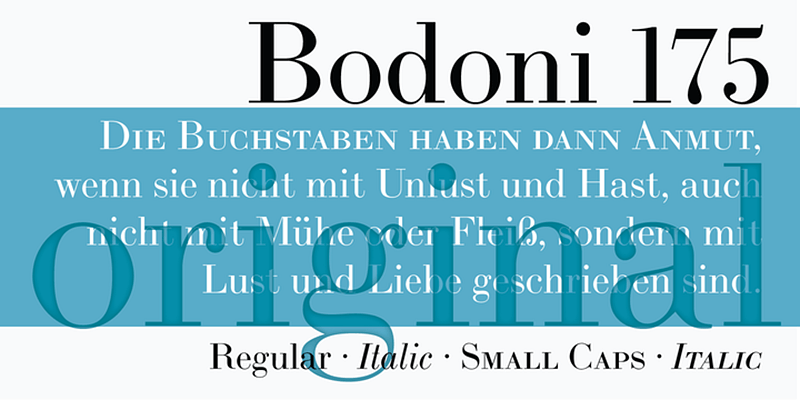
Die LTC Bodoni 175 ist eine moderne Schrift, die ursprünglich von Giambattista Bodoni im Jahr 1790 geschaffen wurde und die als strukturelles Modell für diese originalgetreue Wiedergabe von Sol Hess diente.
Die Wurzeln von Lanston Type Co. (LTC) gehen auf die Lanston Monotype Company von 1887 zurück, die von Tolbert Lanston, dem Erfinder der Monotype-Gießmaschine, gegründet wurde. Nach der Trennung von seinem englischen Pendant hatte LTC Probleme und wurde mehrmals verkauft, an American Type Founders, Hartzel Machine Works, Mackenzie & Harris und Gerald Giampa. Im Jahr 2004 übernahm P22 Type Foundry die Firma und beherbergt heute klassische Designs von Frederic W. Goudy und Sol Hess sowie die neueren zeitgenössischen Meister Giampa, Jim Rimmer und Dave Farey.